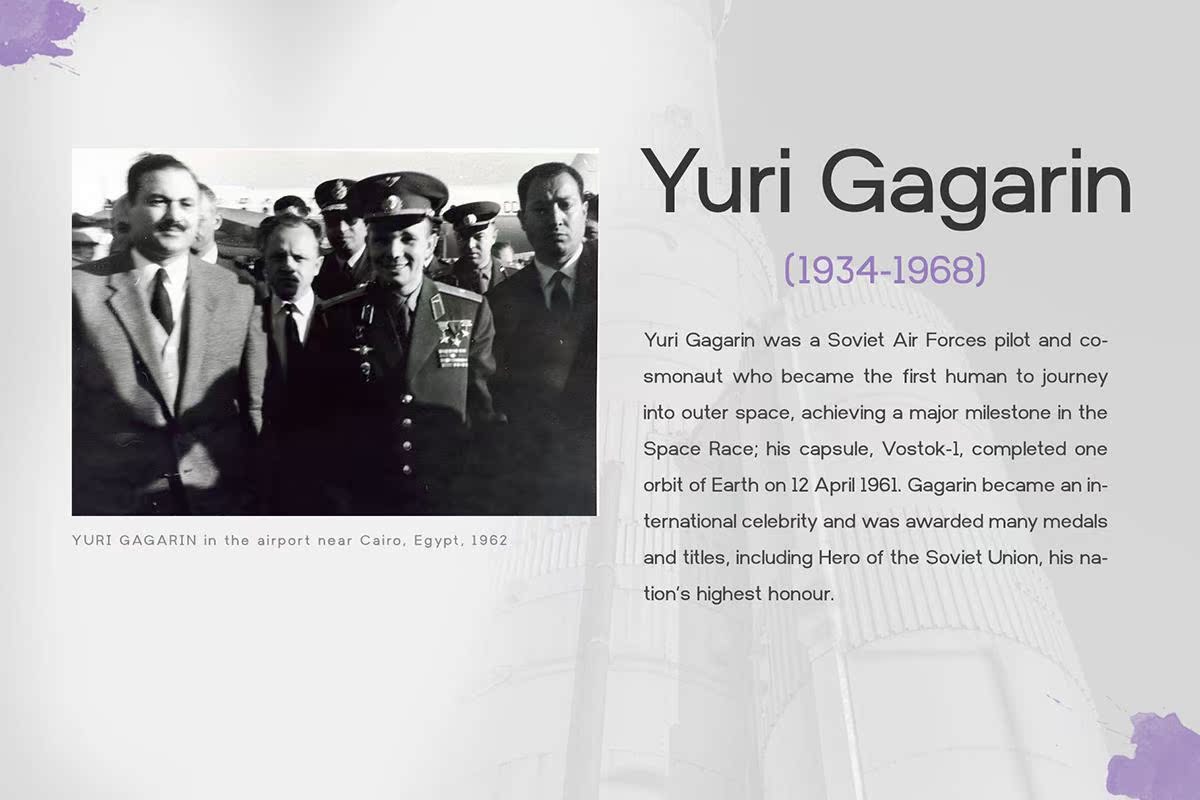
Kronstadtsansseriftypeface是一种锐利的、强有力的无seriftypeface。受宽大字体的启发,Kronstadtis的设计严格且经过认证地包含在标志牌上的徽标中,InFashion Magazines。你可以看到Kronstaddilla非常适合于网站设计,以使你的头条线或字体更加明亮和锋利。宽的大写字母非常适合于剪贴画或按钮。不要忘记边框和几何图形。主文本外观适合阅读。这对图形设计来说是非常重要的,是的!它看起来非常时尚和有组织。只需将其与一些ScriptFont相结合,您的设计项目就会有2020年的前景。